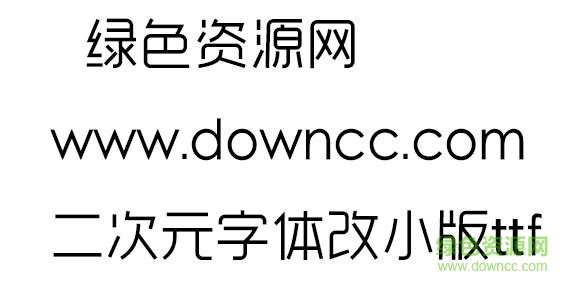
二次元字體改小版
二次元字體改小版ttf為用戶們帶來了最美的二次元字體,這款通過不錯(cuò)的字體格式設(shè)計(jì)出來進(jìn)行了字體改小,讓你能夠感覺到更加不錯(cuò)的視覺效果,這款字體將能夠讓你運(yùn)用到眾多的行業(yè)中,同時(shí)也可以在二次元聊天彈幕制作以及字母制作過程中帶來不錯(cuò)體驗(yàn)!
二次元字體縮小版ttf小編點(diǎn)評(píng)
用了一下二次元字體還是覺得縮小版的更有韻味,更喜歡這款字體,通過使用這款字體,小伙伴們都問我要字體文件,真的挺好看的呢!
二次元字體縮小版字體介紹